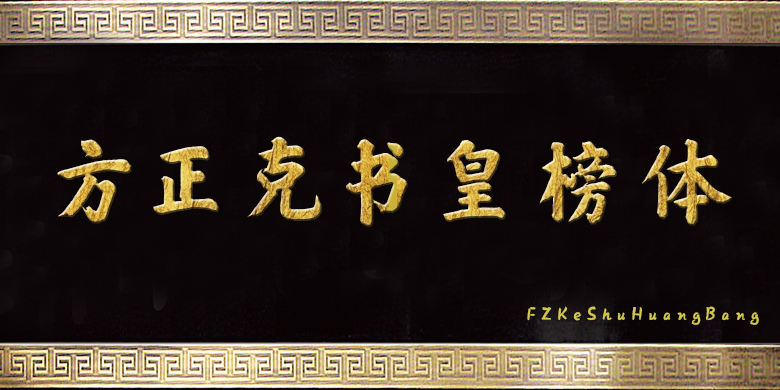
方正克书皇榜体
字体品牌: 方正字库 设计师:刘克 字体分类:楷书 字体属性:精品字 字符集:大陆简体(GB2312-80)、简繁扩展(GBK) 发布时间: 2018
方正克书皇榜体简是由方正字库2018年开发出品的一款中文字体,作者刘克(克叔),北京人。自称传统书法爱好者,一个小小写字匠。该 字体设计以颜体多宝塔、勤礼为基底,融入了宫廷匾额的雍容、端正,求绵润,绵中带力。不张扬,不嚣张,不做作,不浮夸,不求怪,不求险峻。与宫廷对联比较,单字纵向稍作收敛,求方正,便于横竖排版。
特别适用于:对联、门头字号匾额、大海报;中国风的产品,中国传统节日广告等。